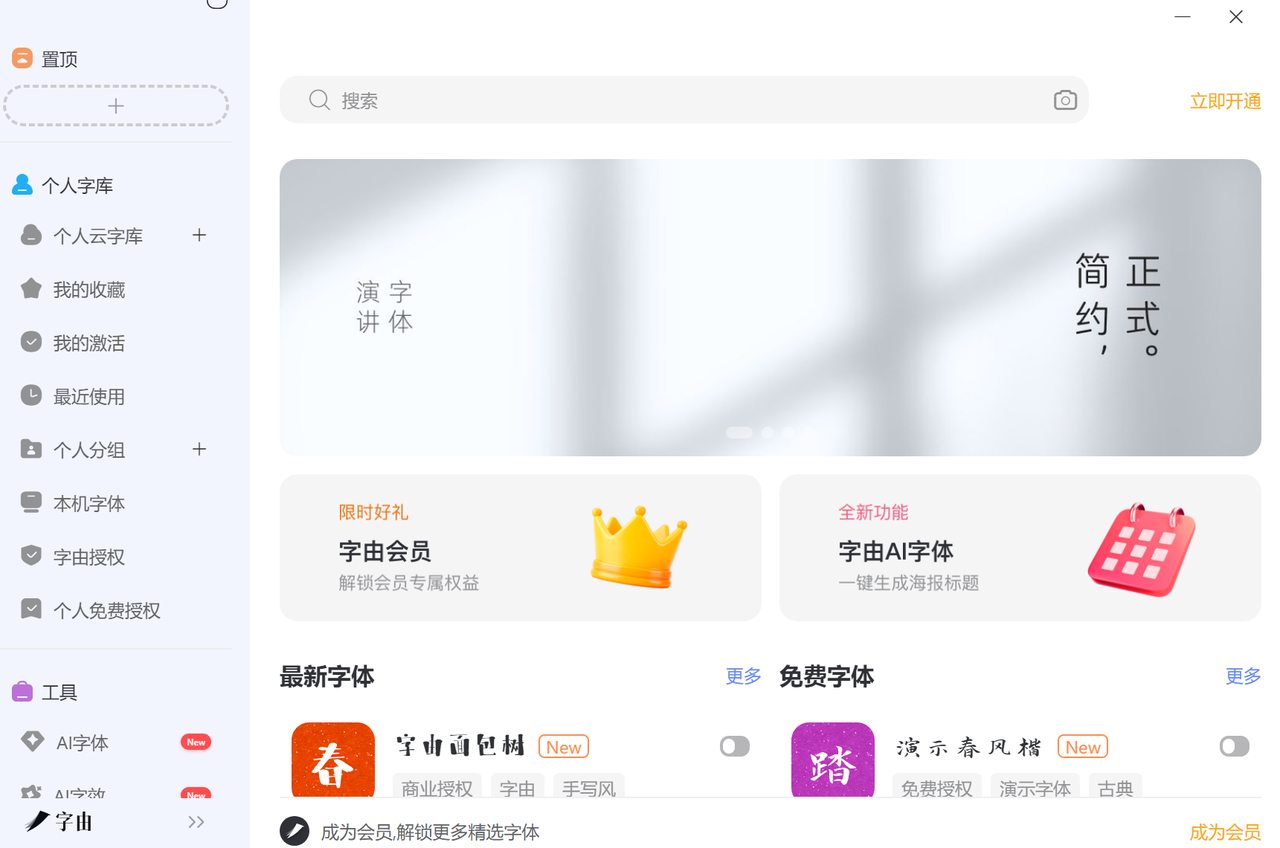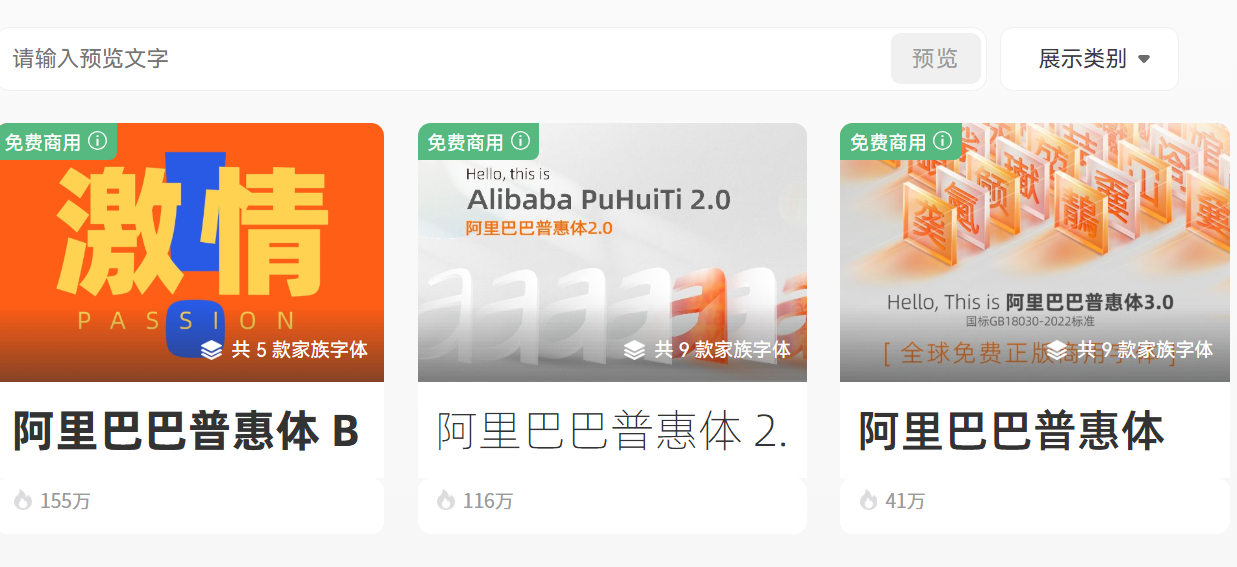
零成本做设计!推荐4 个免费字体网下载,新手也能用
做设计的人都懂那种感觉:配色调好了,排版也顺眼了,偏偏字体不对——整张图就像穿了一件不合身的衣服,看着哪哪都别扭。更麻烦的是,网上随手下载的字体,用着用着就收到律师函。字体版权这潭水,比大多数人想象的深得多。方正、汉仪、华康……这些耳熟能详的字体家族,商用一张图的授权费少则几百,多则上千,对刚起步的设计师或者小预算的内容创作者来说,根本不现实。但好消息是:免费可商用的优质字体,真的存在,而且不少。本文推荐的这4个网站,是我反复筛选、实际用过之后留下来的,每个都有自己的特点,按需取用就好。
字由网
如果只推荐一个字体网站,我会毫不犹豫选字由。原因很简单:它不只是个"下载网站",它是一个字体管理工具。下载客户端之后,你不需要把字体一个个解压安装到系统里,字由会帮你统一管理,直接激活,干净利落,电脑也不会因为装了几百个字体而越跑越慢。字由支持 Windows 和 macOS 双平台,安装完客户端之后后台常驻,几乎感觉不到它在运行,但每次打开 PS、AI、Figma 这些设计软件,所有字体都已经准备好了。体验地址: www.hellofont.cn
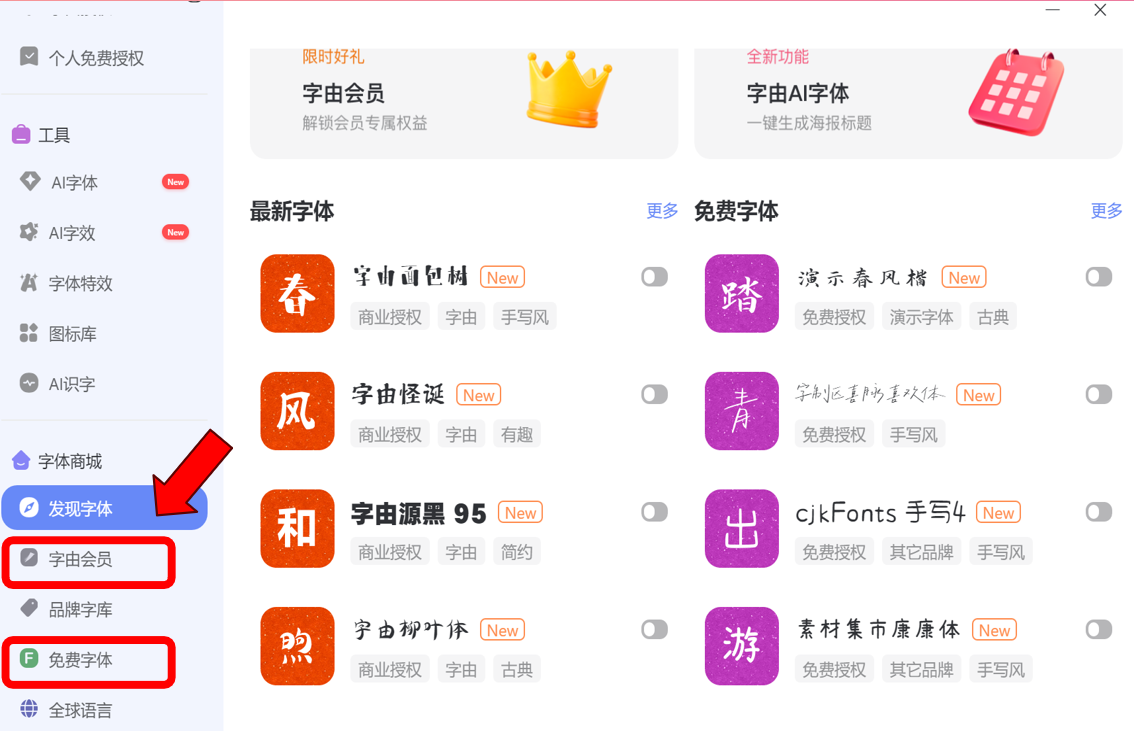
下面重点介绍几款值得收藏的免费可商用字体:
① 站酷系列——站酷旗下出品了多款免费字体,每一款风格差异很大,覆盖的使用场景相当广:
站酷酷黑:适合电商促销主图、活动倒计时海报
站酷快乐体:适合儿童品牌、趣味推文封面、游戏相关内容
站酷文艺体:适合生活方式类内容、公众号封面
站酷庆科黄油体:适合美食、生活、萌系内容,辨识度很高
② 阿里巴巴普惠体——这款字体是阿里巴巴专门开发并向全社会开源的字体,一共有7个字重,从极细到超粗都有,适应性非常强。授权范围宽泛,个人和商业用途均免费,不需要额外申请。做PPT、产品介绍页、公众号长图这类需要大段文字的设计,阿里巴巴普惠体是很稳妥的选择。
③ 思源黑体 / 思源宋体——Adobe × Google 联名出品,质量天花板,思源系列是Adobe和Google联合开发的开源字体项目,简单来说就是:由两家顶级公司出钱出技术做的字体,免费给全世界用。
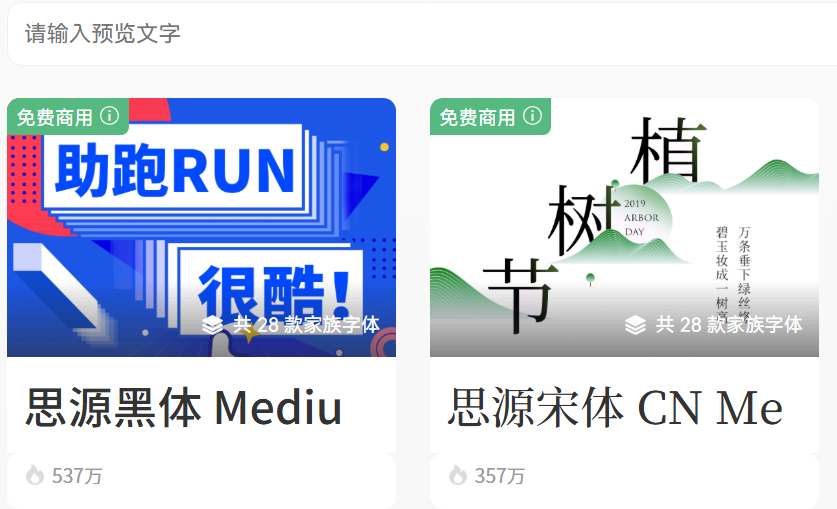
100font
如果你不想装客户端,只想纯粹下载字体文件,100font 是目前我见过做得最干净的一个。网站的定位非常明确:只收录免费可商用字体,没有付费内容,没有诱导点击,进去就是字体列表,找到喜欢的直接下。字体数量虽然不算海量,但胜在质量把控不错,收录的基本都是有明确授权声明的字体,商用风险相对低。
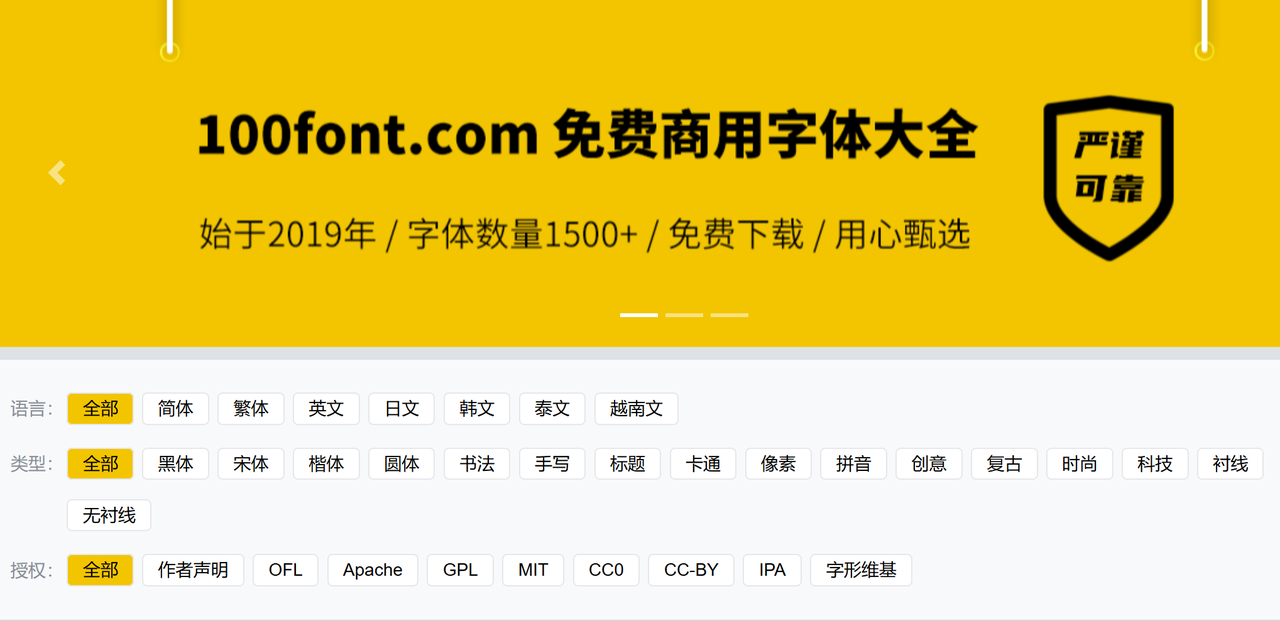
Google Fonts
做国际化项目、英文内容,或者中英混排设计的话,Google Fonts 几乎是绕不开的存在。对设计师来说,Google Fonts 还有个隐藏优势——它的字体配对推荐功能。你选了一个标题字体,它会自动推荐几款与之协调的正文字体,对字体搭配没概念的新手来说,这功能几乎是救命的。中文支持方面,Google Fonts 也在持续扩充,思源黑体、思源宋体、Noto 系列都在里面,中文场景同样可以用起来。
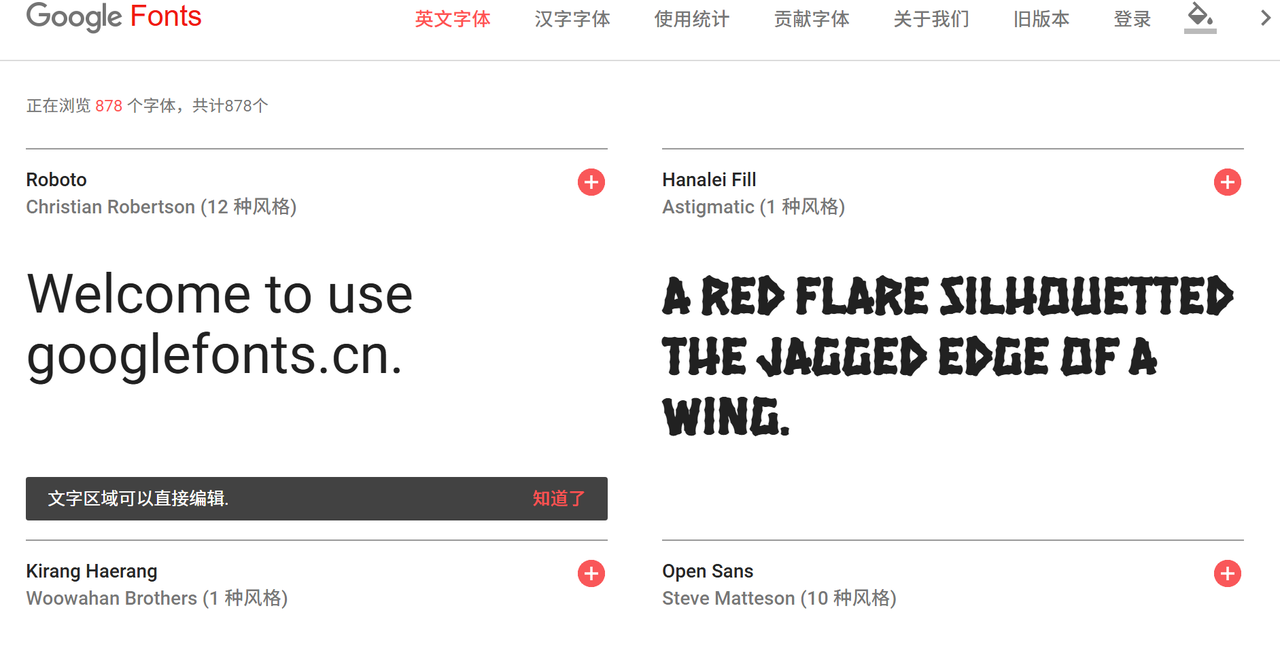
Fontsquirrel
Fontsquirrel 在英文设计圈的地位,有点像字由在国内字体圈的地位。它的选字逻辑和 Google Fonts 略有不同:Fontsquirrel 更偏向手工艺感、复古风格、个性化字体,适合品牌视觉设计、Logo 制作这类需要差异化的场景。另外,Fontsquirrel 有一个实用功能很多人不知道——Webfont Generator,可以把你手上的字体文件转换成网页可用的格式(woff、woff2 等)。